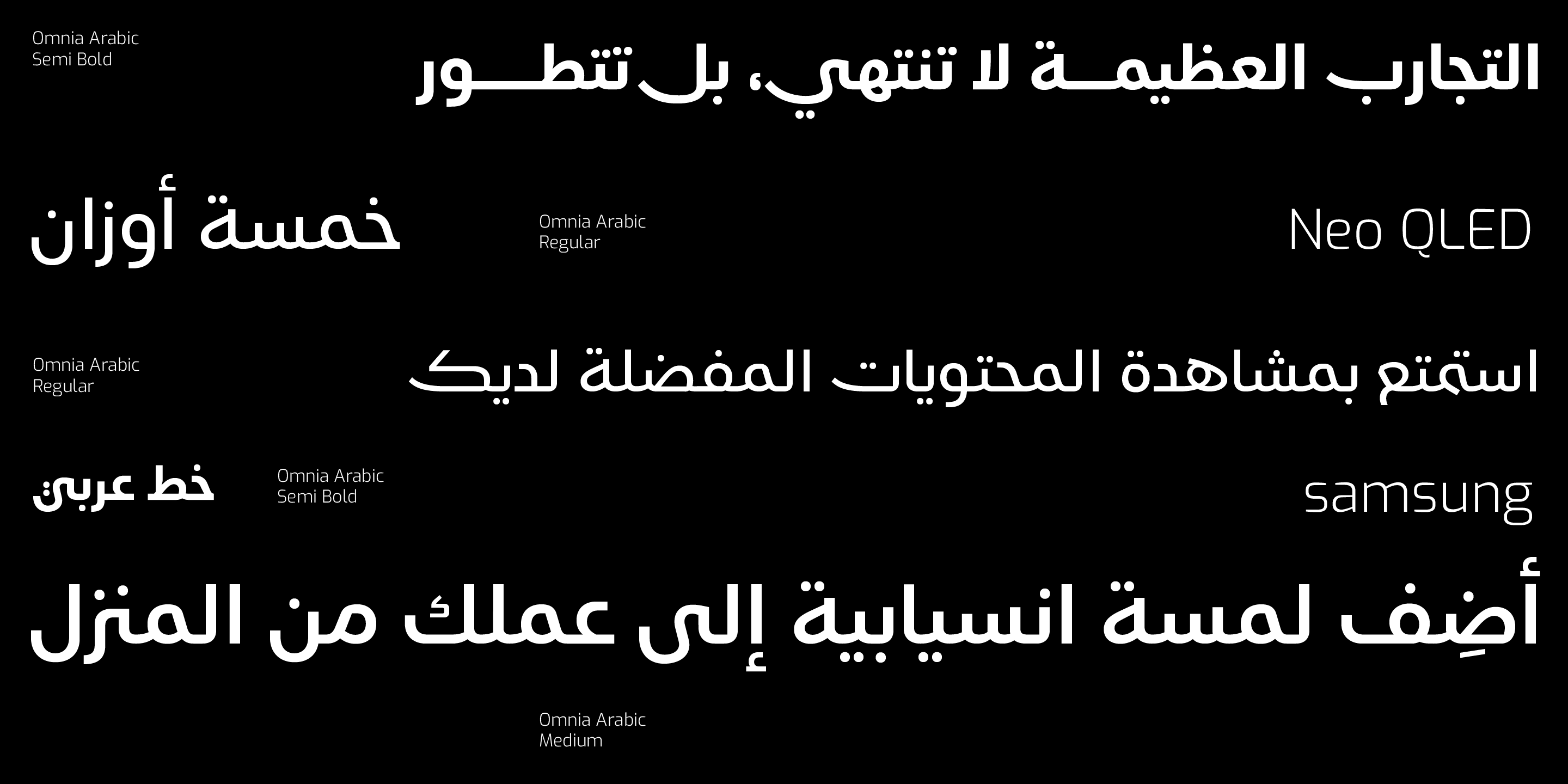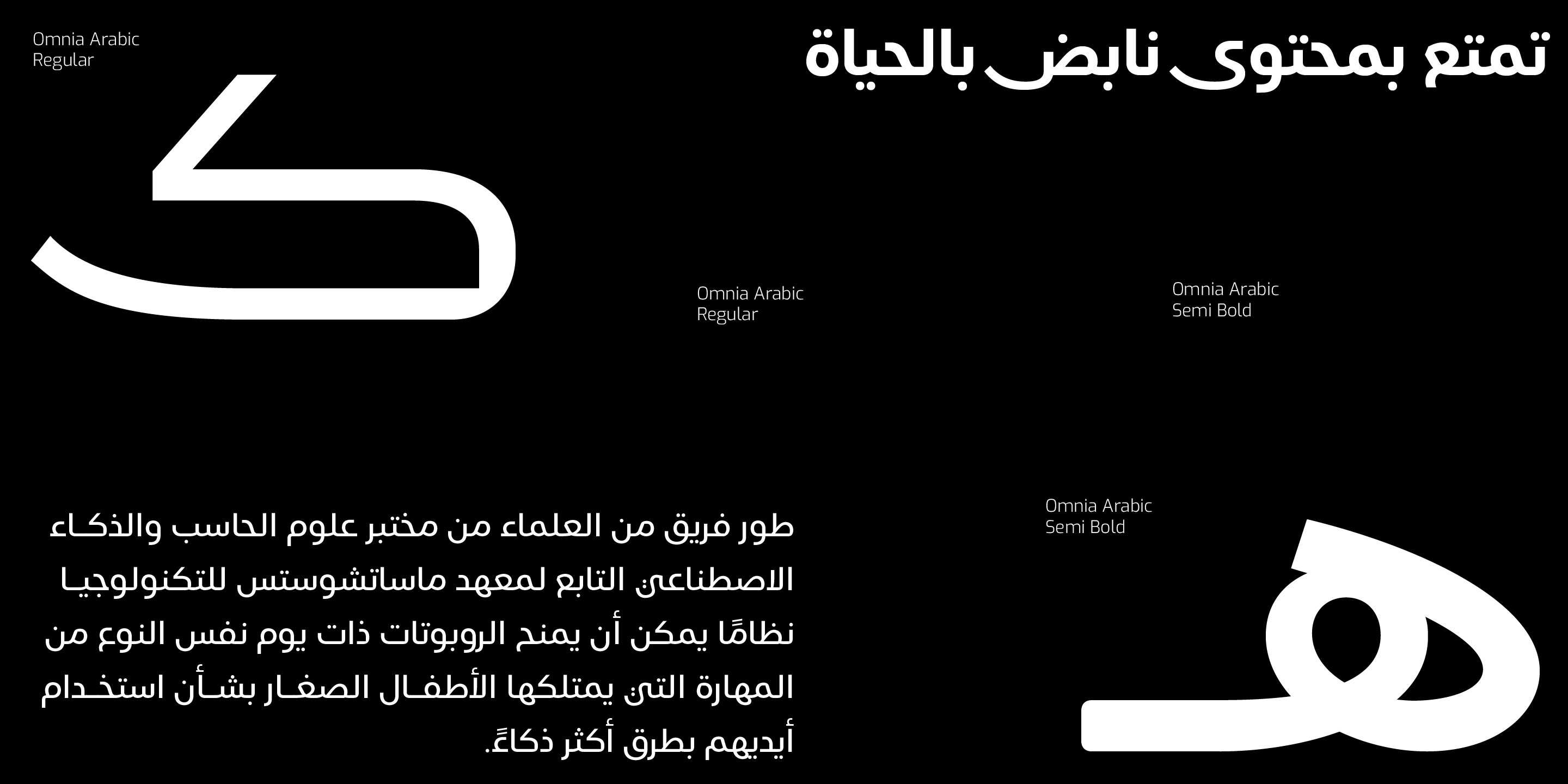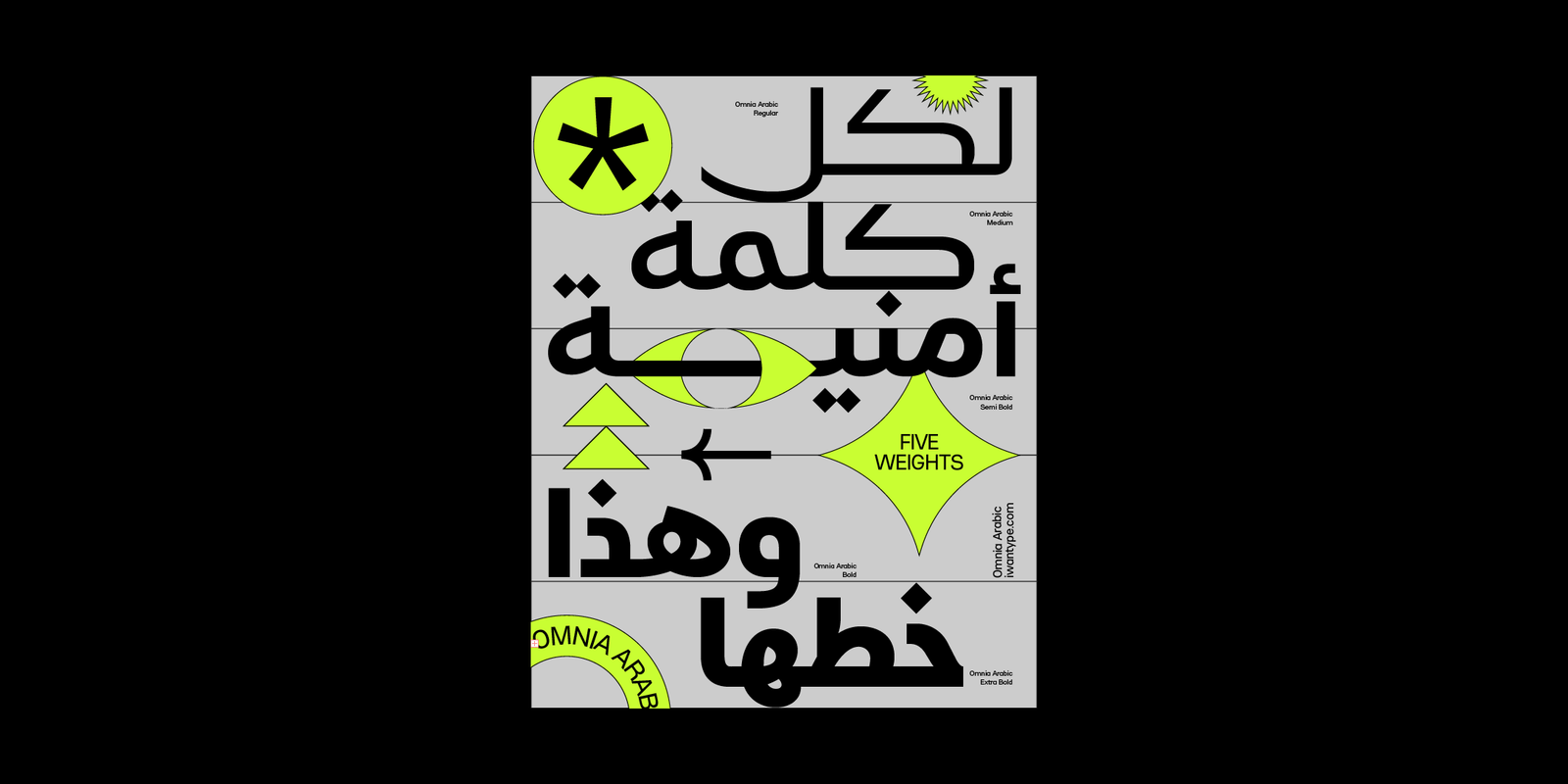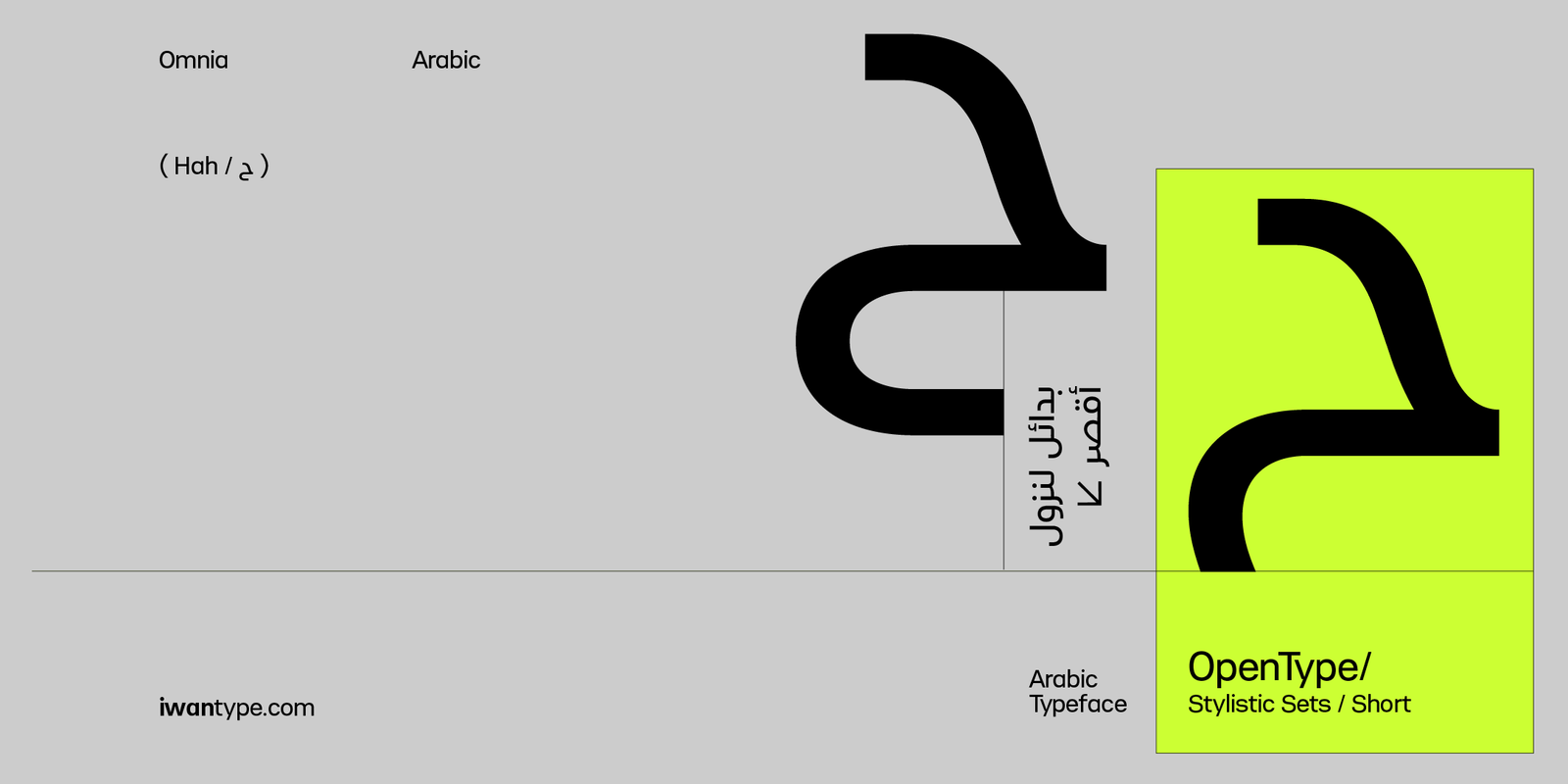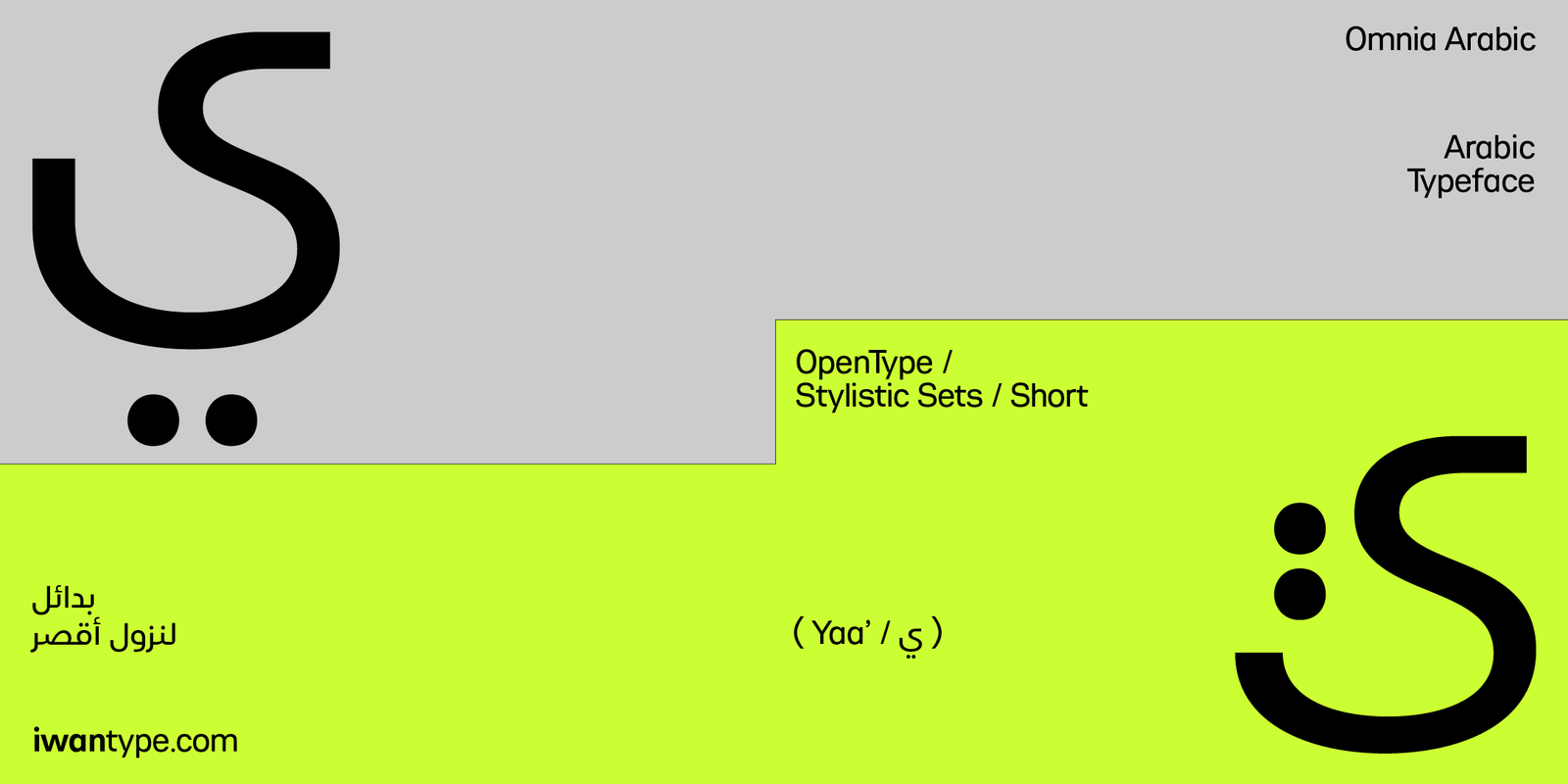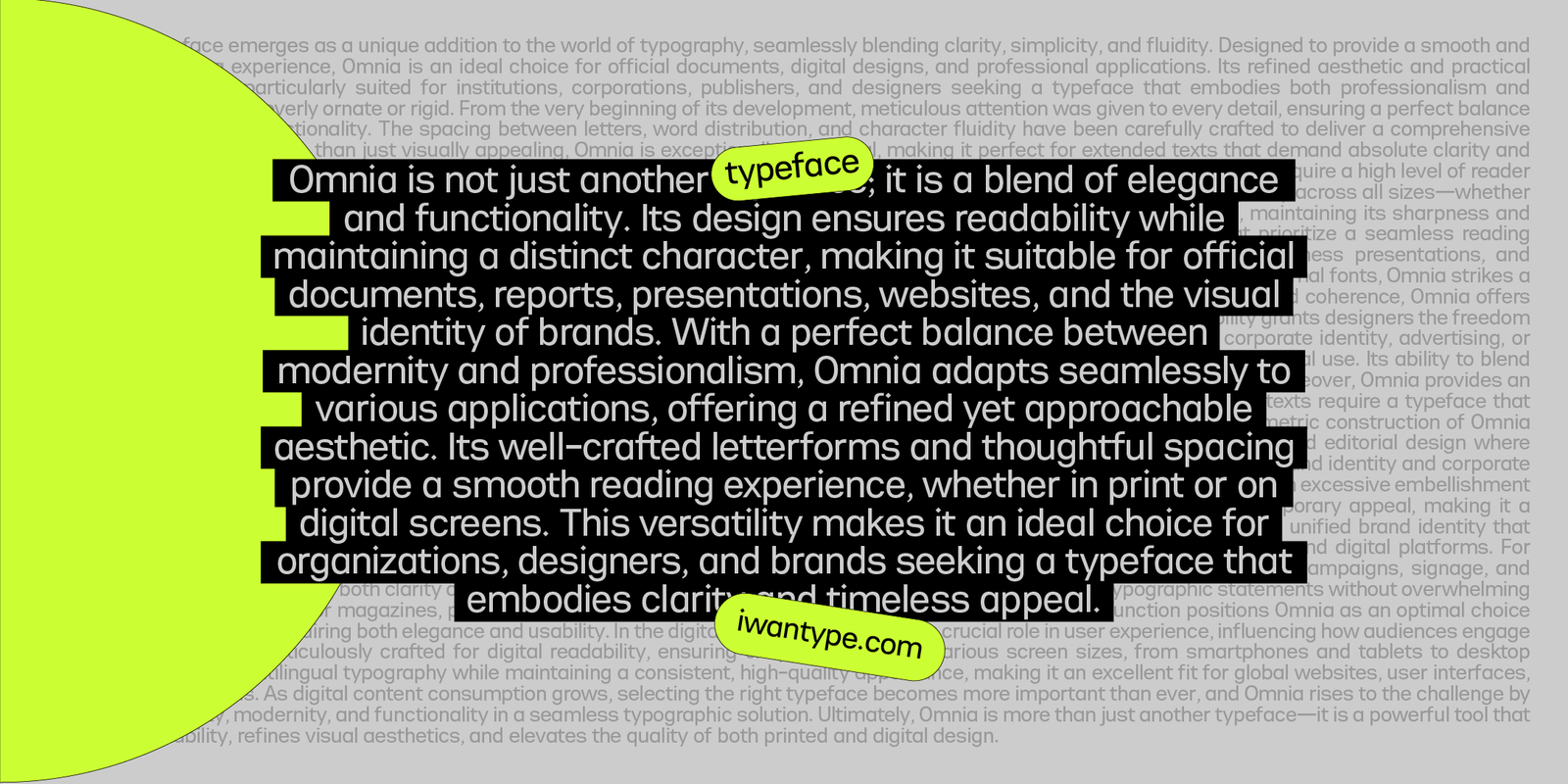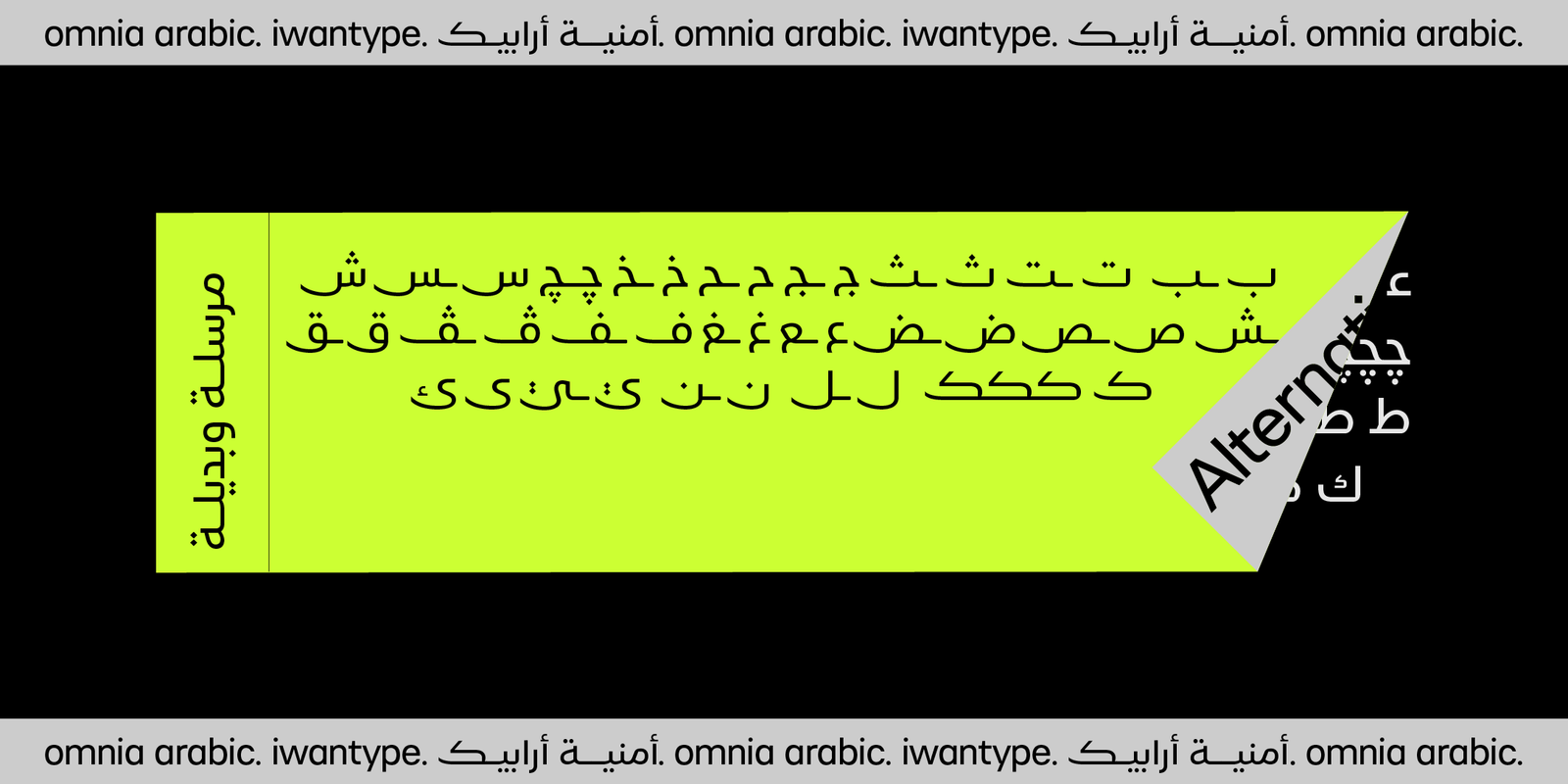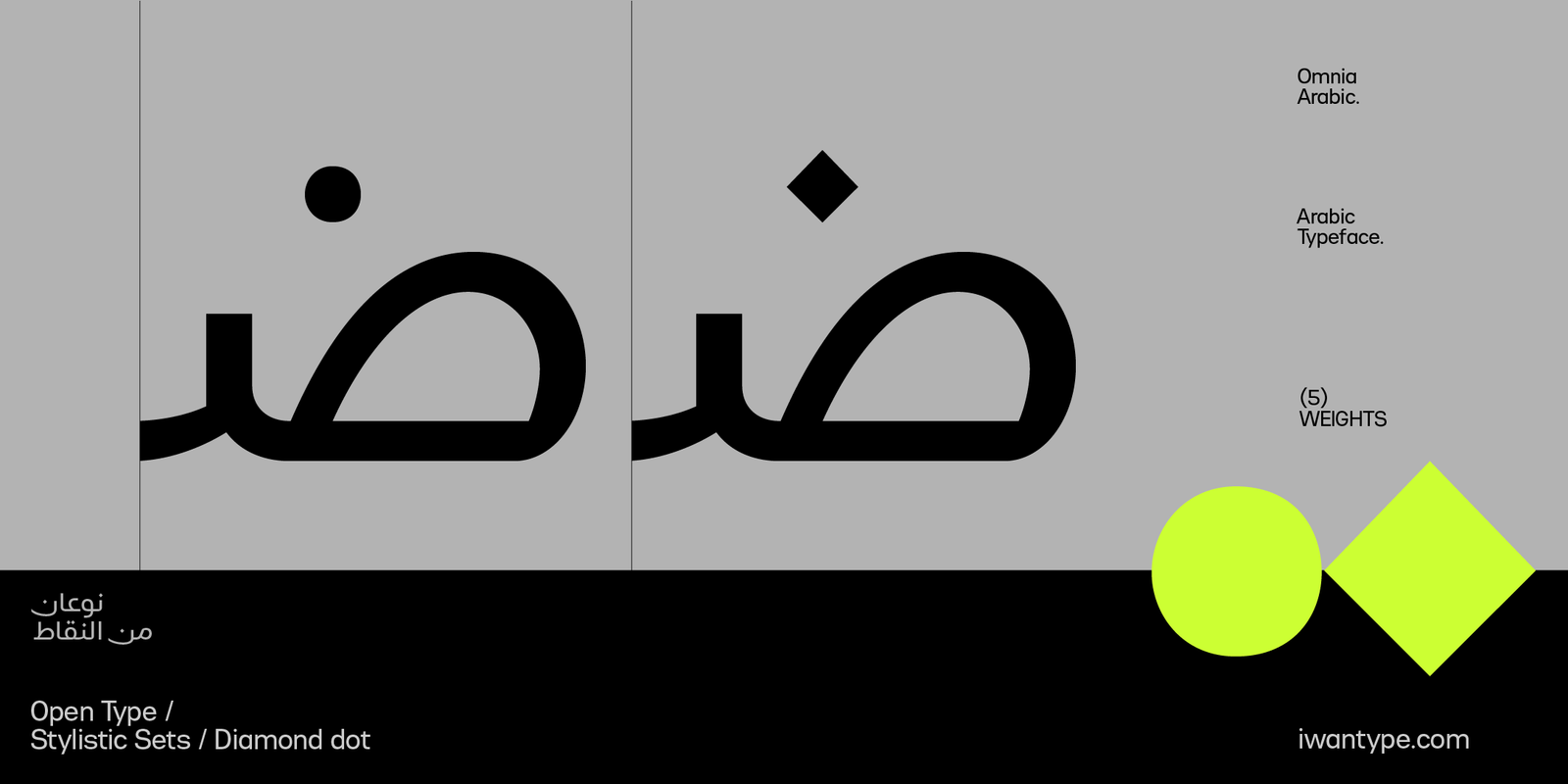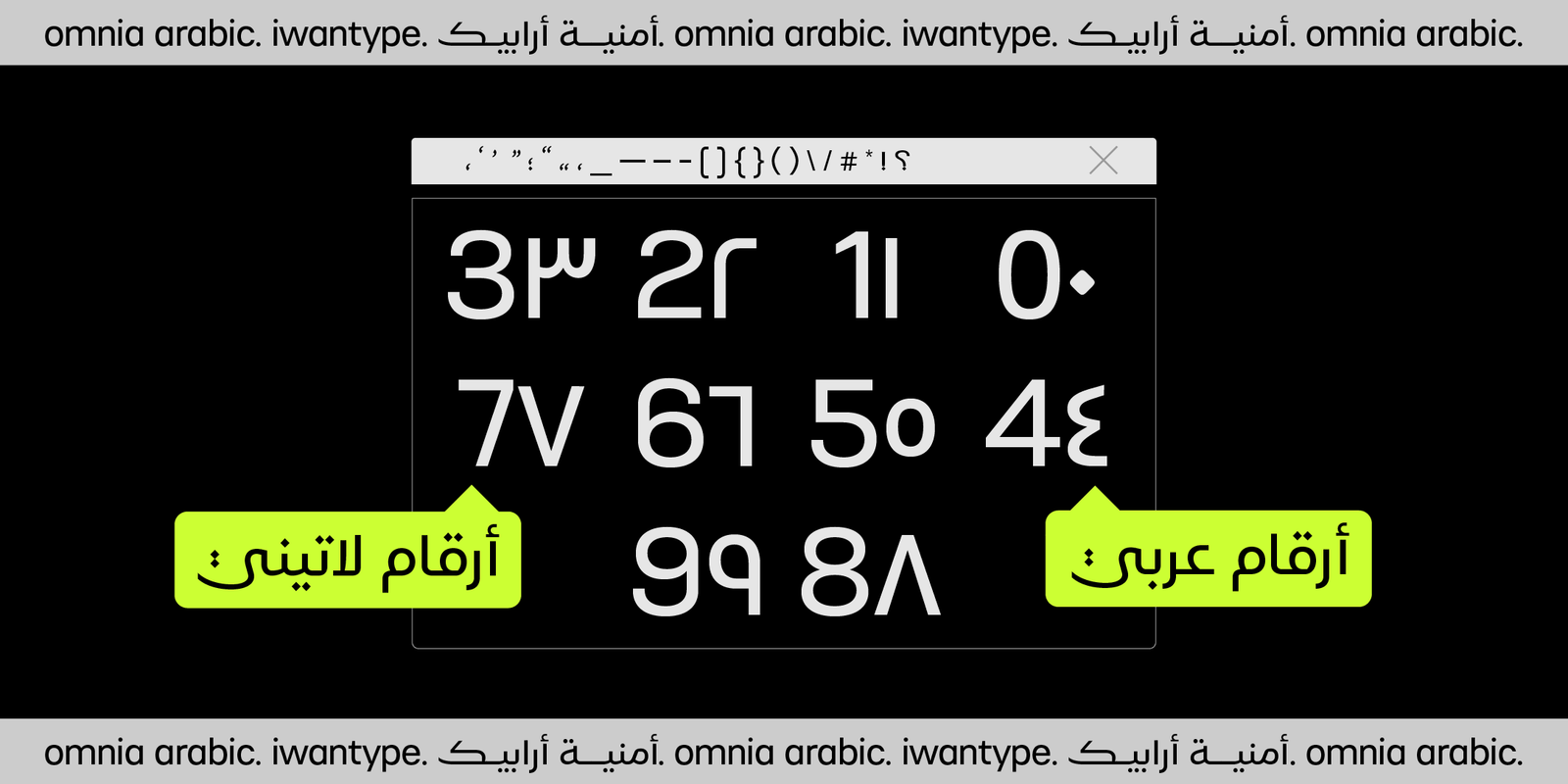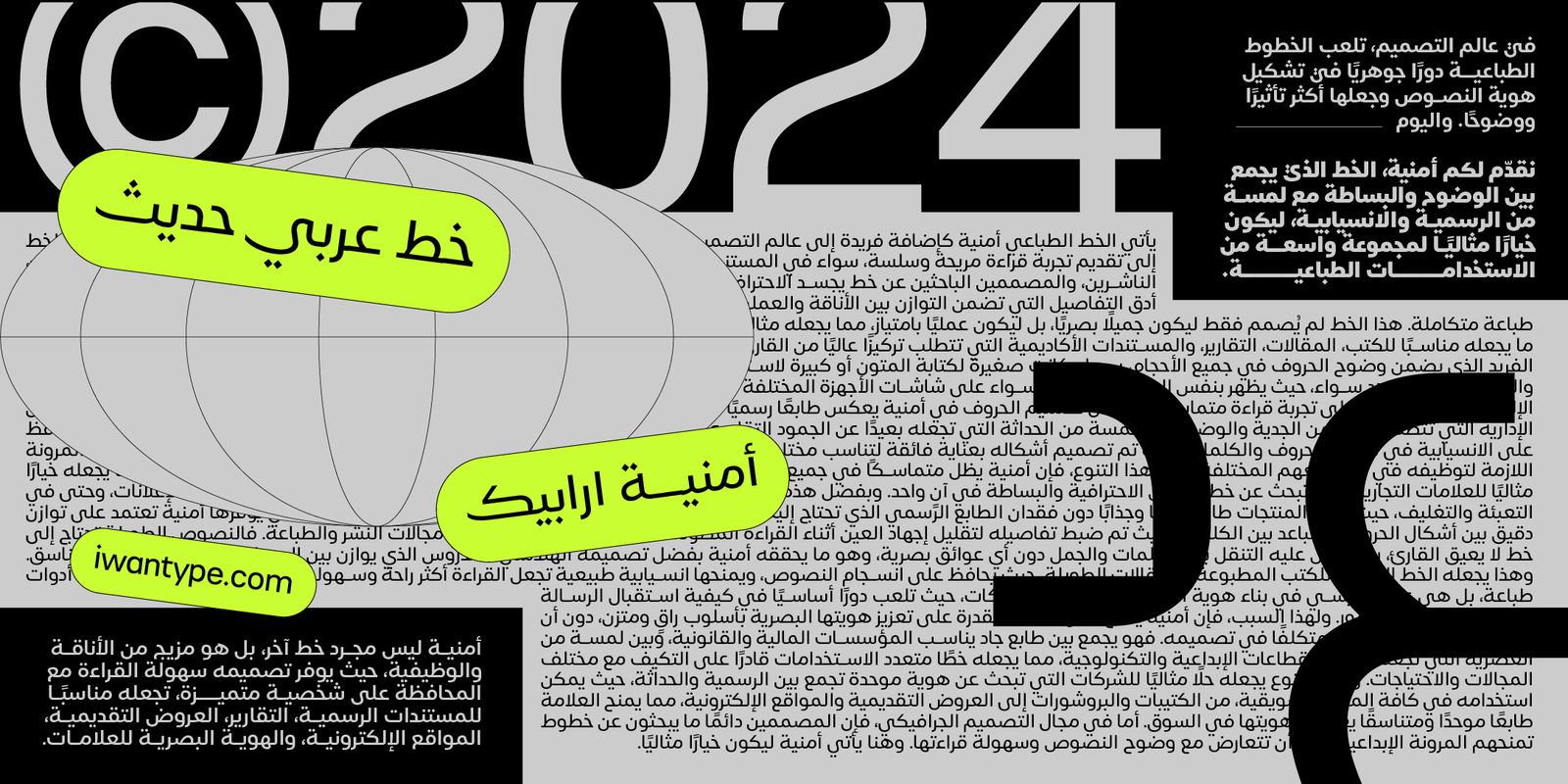
Omnia Arabic typeface – خط أمنية ارابيك
أمنية أرابيك هو خط عربي يجسد جوهر الأناقة والانسيابية. وهو مزيج متناغم من المنحنيات الرشيقة والجماليات الرائعة، تم تصميمه ليأسر ويلهم.
فلسفة التصميم الأساسية لأمنية أرابيك ترتكز على الدمج السلس بين المنحنيات، حيث يتدفق كل خط بانسيابية إلى الخط التالي. والنتيجة هي نظام كتابة ينقل إحساسًا بالحركة السهلة والجمال الفطري، مما يعكس جوهر تدفق الخط العربي الطبيعي.
إحدى الميزات الأكثر تميزًا في أمنية أرابيك هي مجموعة ميزات OpenType الواسعة. توفر هذه الميزات عالماً من الإمكانيات، مما يمكّن المصممين والمستخدمين من تحقيق رؤاهم الإبداعية. يتميز أمنية أرابيك بمجموعة من الحروف البديلة، مما يتيح تنوعًا في الحروف يلبي احتياجات التصميم المختلفة. يقدم كل بديل مجموعة رائعة من الخيارات لتعزيز التعبير الطباعي الخاص بك.
يتوفر أمنية أرابيك في خمسة أوزان مصممة بدقة، مما يوفر تنوعًا ومرونة للتكيف مع أي سياق تصميمي. سواء كنت تبحث عن لمسة رقيقة في الوزن الخفيف أو بيان جريء في الوزن الثقيل، يضمن أومنيا أرابيك أن كل تمثيل بصري يحافظ على سحره ورقيه.
اللغات : العربية والإنجليزية
الاوزان : خمسة اوزان